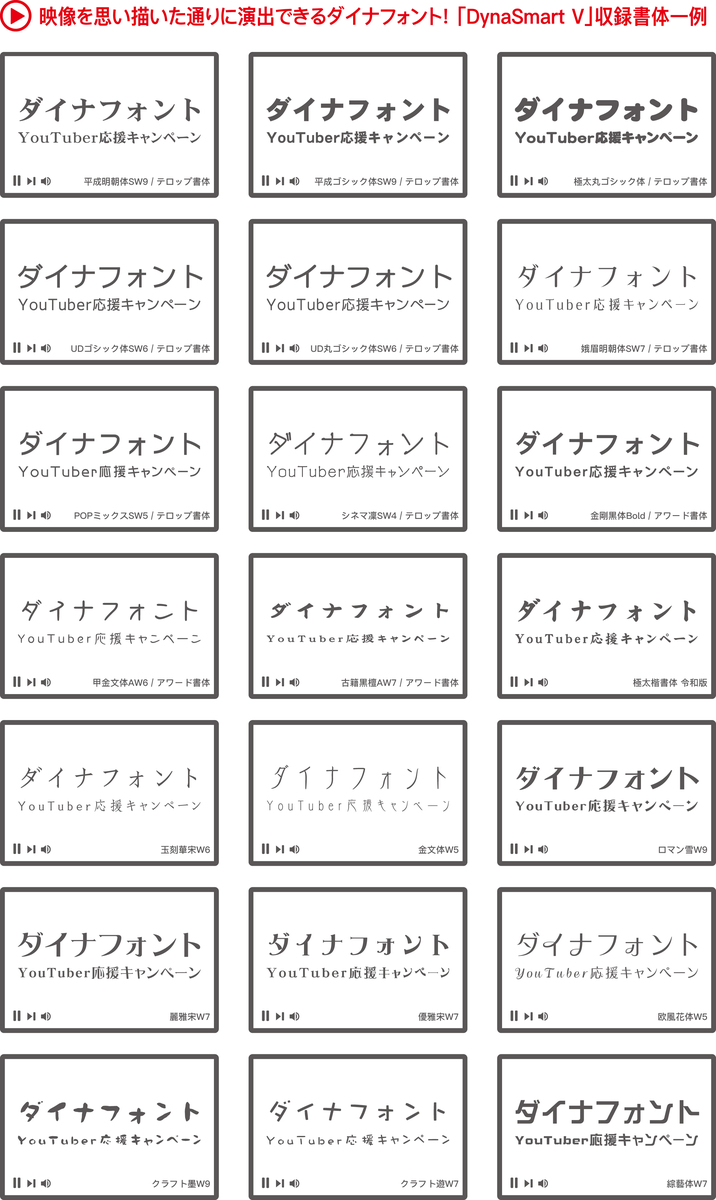
YouTube動画制作にもオススメのダイナフォント製品「DynaSmart V」
ダイナコムウェア株式会社が提供する「ダイナフォント」は、映像業界において、映画、テレビ番組、CM、デジタルサイネージ、ビデオ、DVD、ストリーミング動画投稿サイトなどでのテロップやメニュー画面など、様々な用途で採用され、実績を積み重ねており、2022年となる現在においても映像クリエイターに愛用されている。
その理由として、ベーシックなゴシック体・明朝体から、伝統的な筆文字、新感覚なデザイン系の筆文字や人の手の温もりを伝える手書き風文字、あらゆる画面サイズで視認しやすいように考慮して従来の書体を再設計したテロップ書体、それ以外にもバラエティに富んだ数多くのデザイン系書体など、高品質で幅広い書体ラインナップを揃えていることが挙げられる。